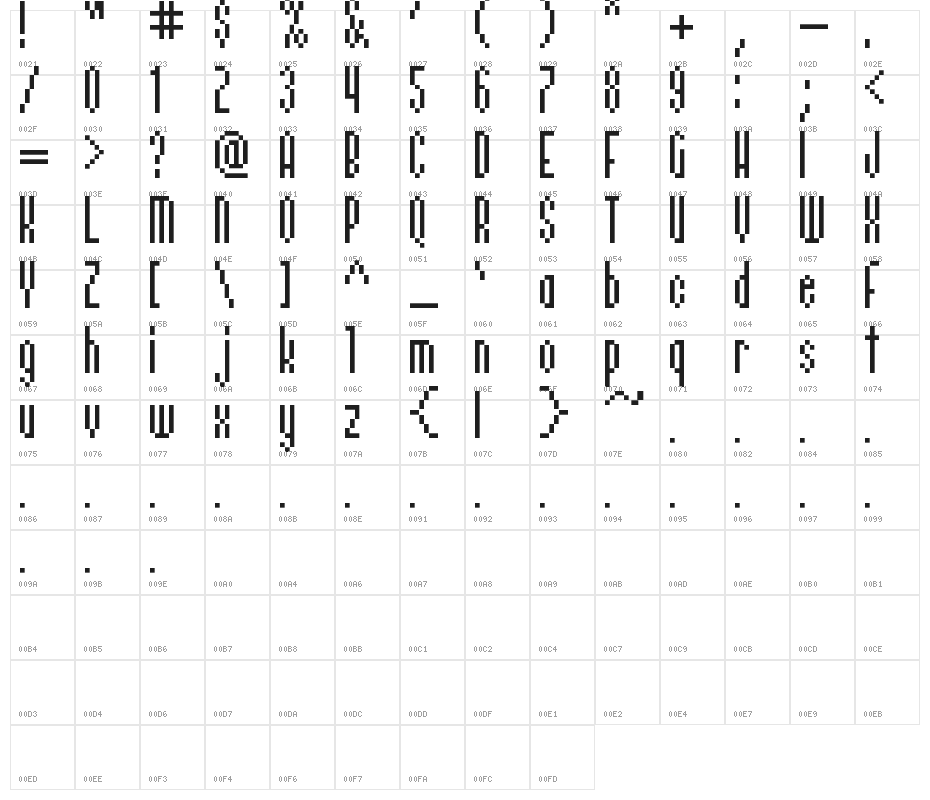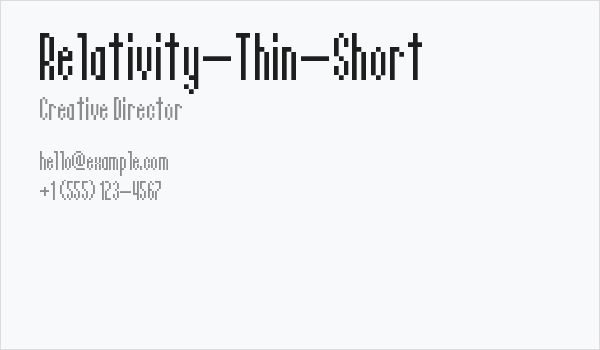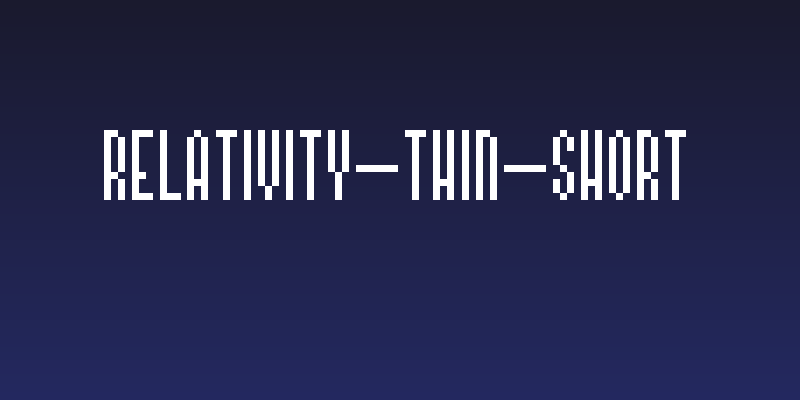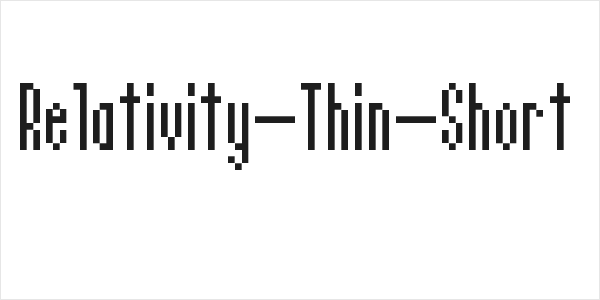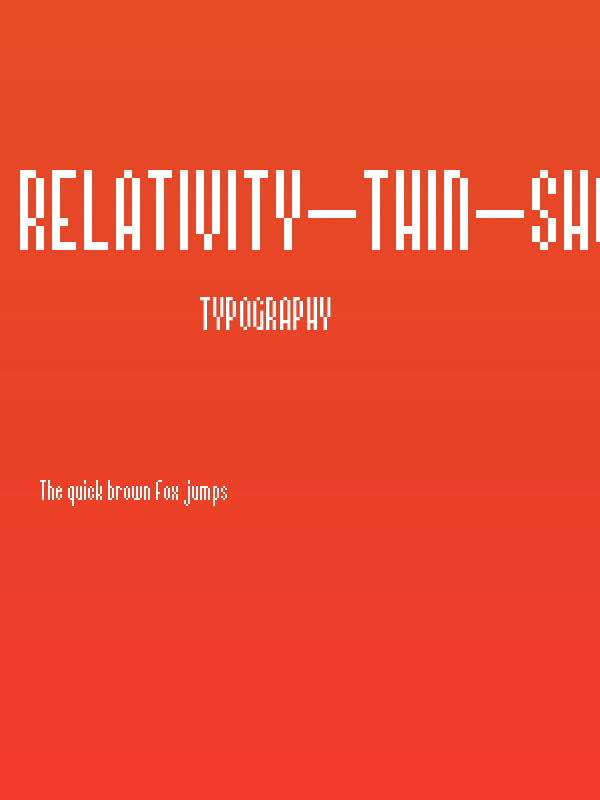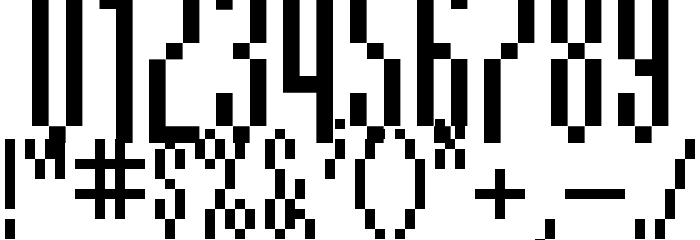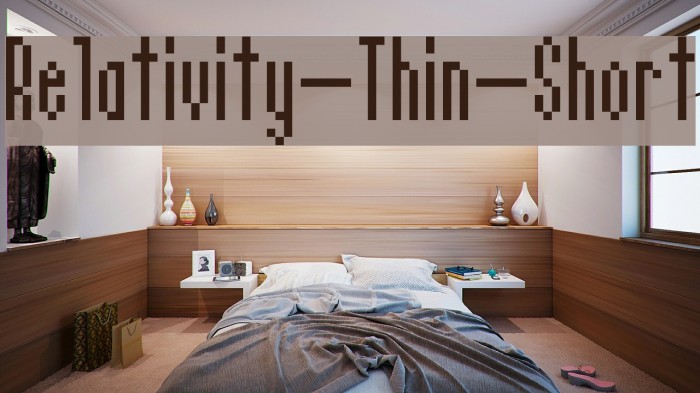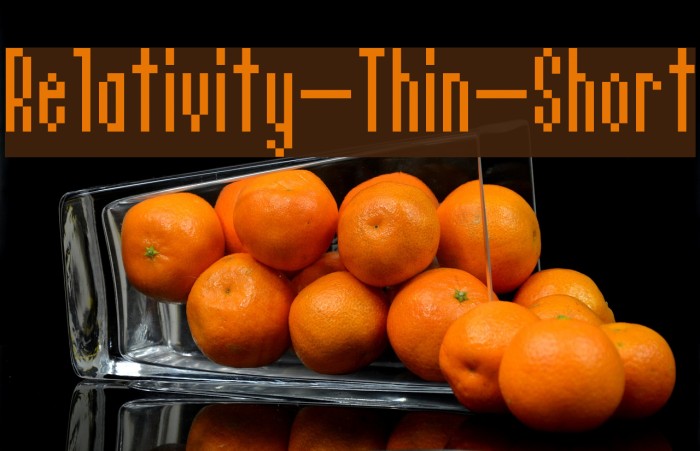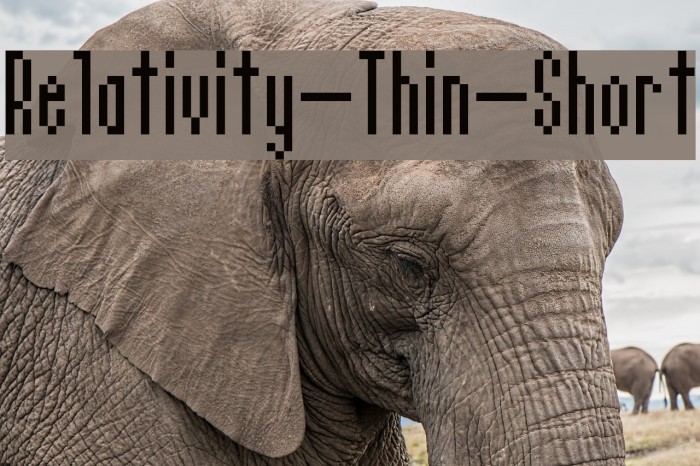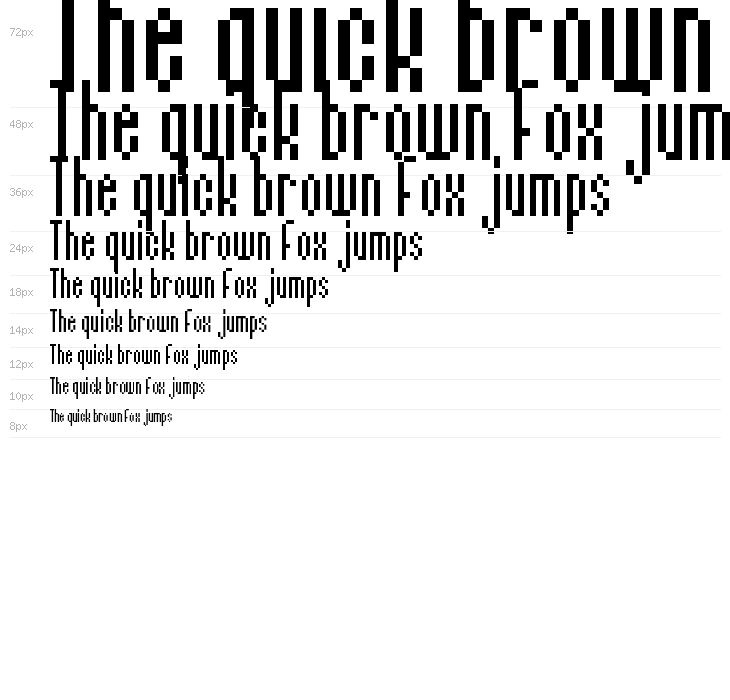
Relativity-Thin-Short Font
| Caso de uso | Logos, Headlines, Digital interfaces |
| Proyectos propuestos | Ideal for digital art projects, retro-themed designs, video game interfaces, and tech-related branding. |